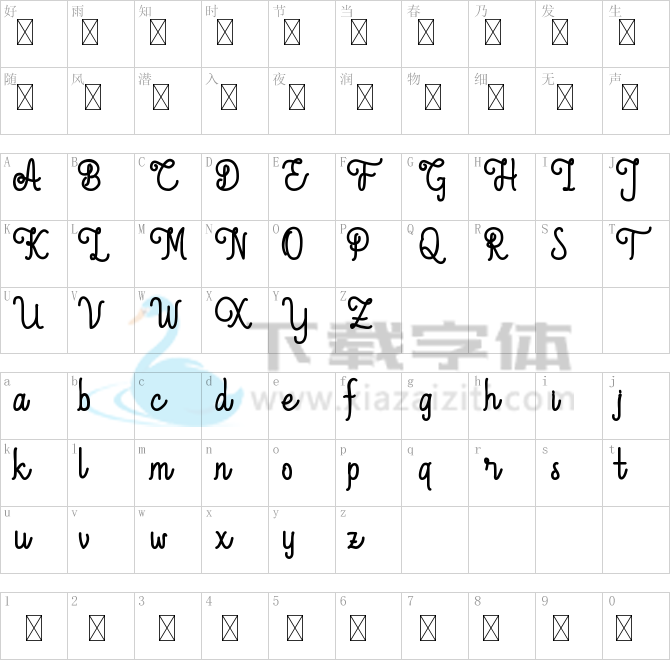
Aleda Demo Monoline Bold.ttf字体下载,这款字体结构工整、笔画清晰,兼顾美观与易读性,适用于标题、正文、海报、包装、LOGO 等多种场景。字形优雅稳定,风格百搭耐看,适配日常排版与创意设计,让文字呈现更舒适、更具质感。Aleda Demo Monoline Bold.ttf字体下载一笔一画,皆是细节,以均衡的比例、流畅的线条打造舒适视觉体验,字形端正大气,风格简约现代。无论是商业设计、品牌宣传还是日常排版,都能轻松驾驭,让文字更有格调与力量。Aleda Demo Monoline Bold.ttf字体下载字体下载。